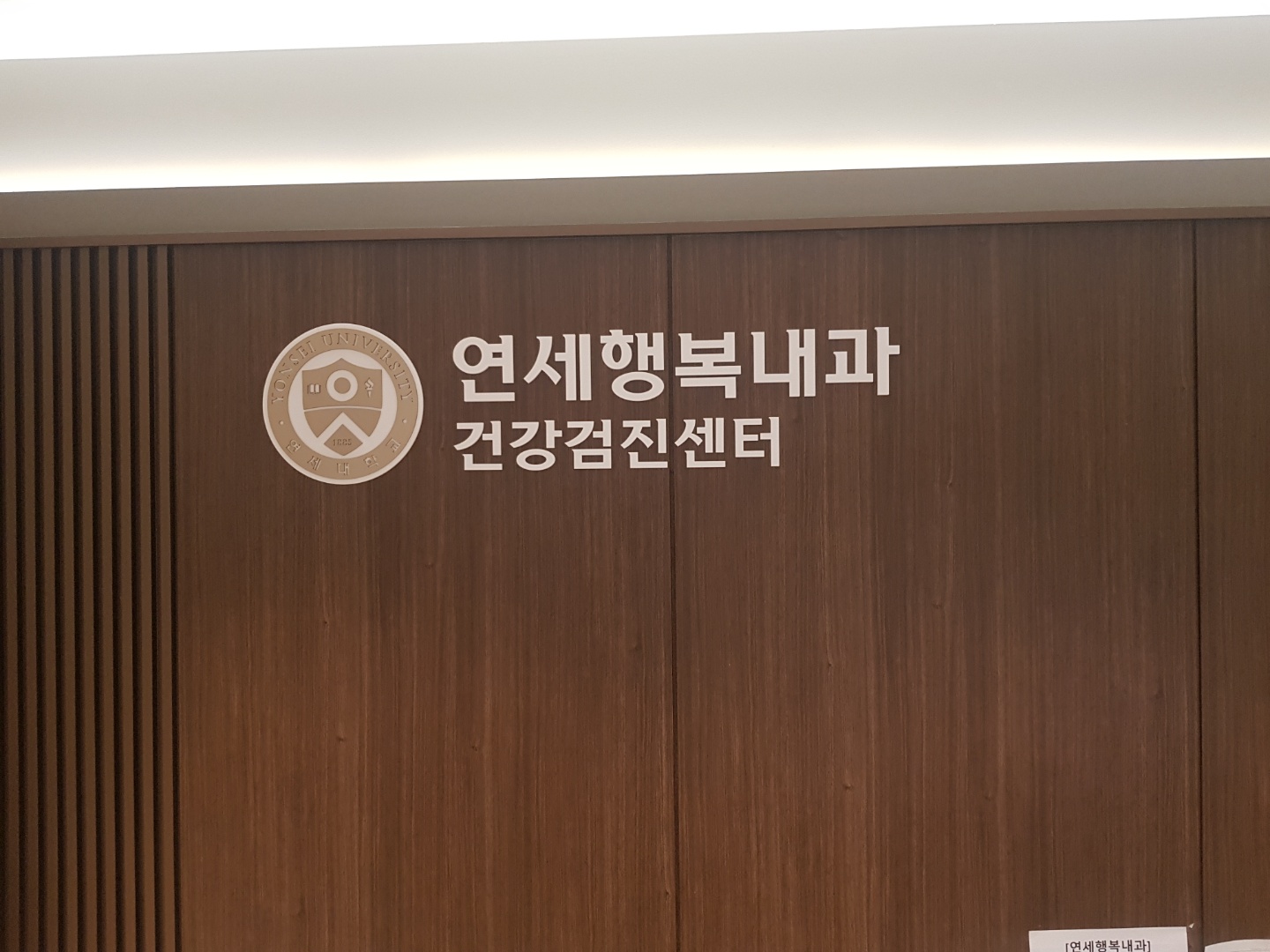
김해가야체 02 Bold
이폰트인줄 알았는데 과 자가 모음자음이 떨어져있는게 다르더라구요
정확한 폰트이름이 알고싶습니다
이폰트인줄 알았는데 과 자가 모음자음이 떨어져있는게 다르더라구요
정확한 폰트이름이 알고싶습니다
연세제목체 같네요. https://www.yonsei.ac.kr/sc/intro/symbol4.jsp